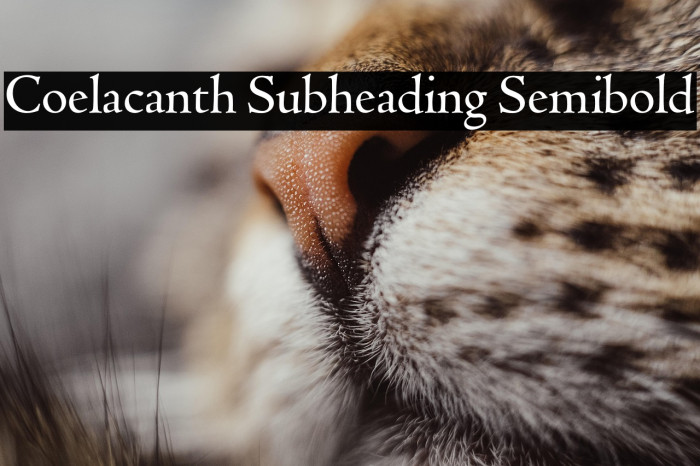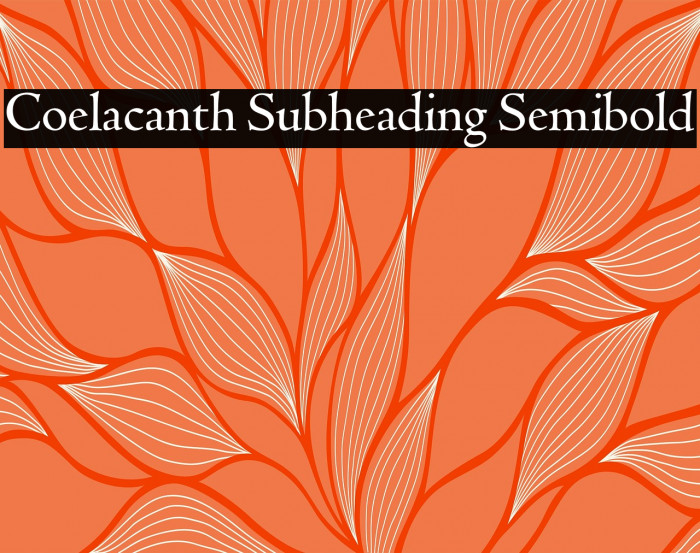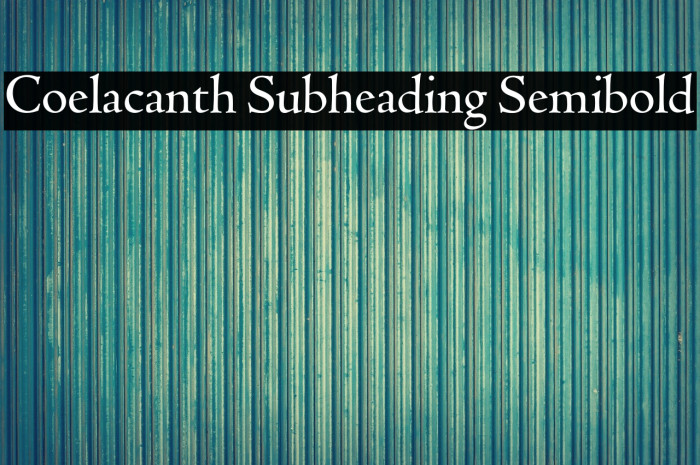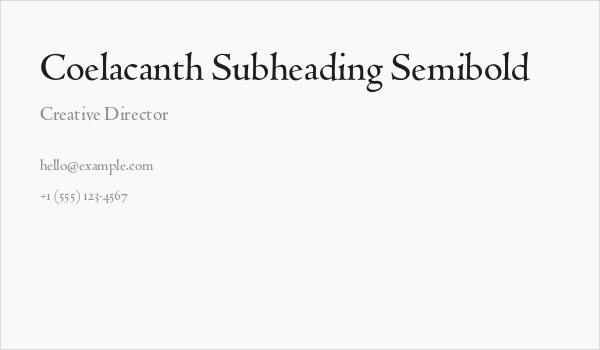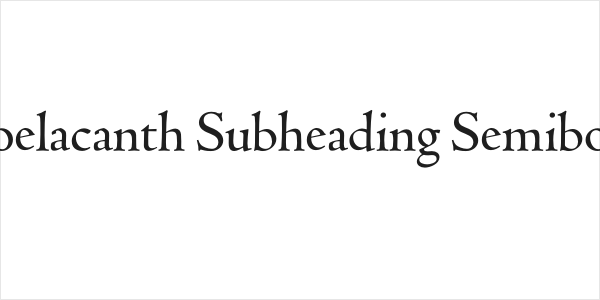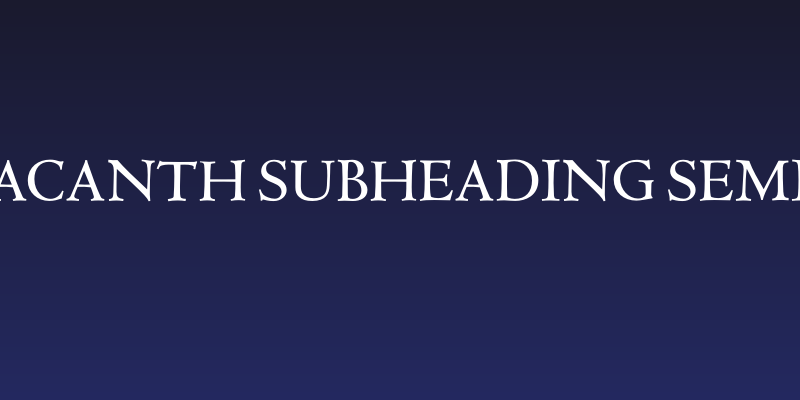
Coelacanth Subheading Semibold Font
✎ Serif
| 分类 | Serif |
| 整体风格 | Classic |
| 使用场景 | Headlines, Subheadings, Branding |
| 推荐项目 | Ideal for editorial design, book covers, branding, and sophisticated invitations. |